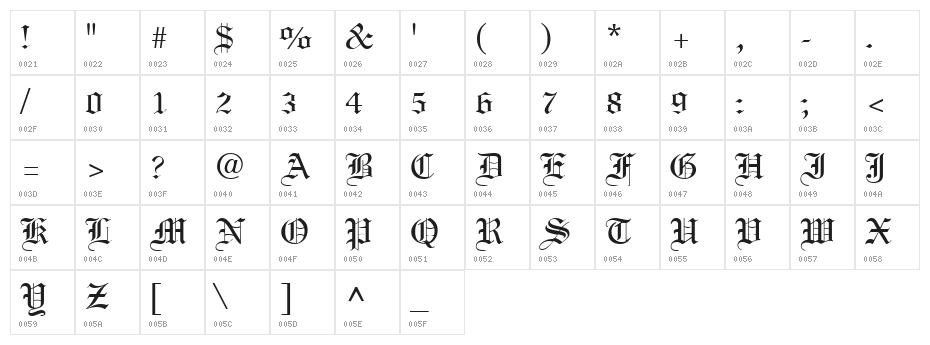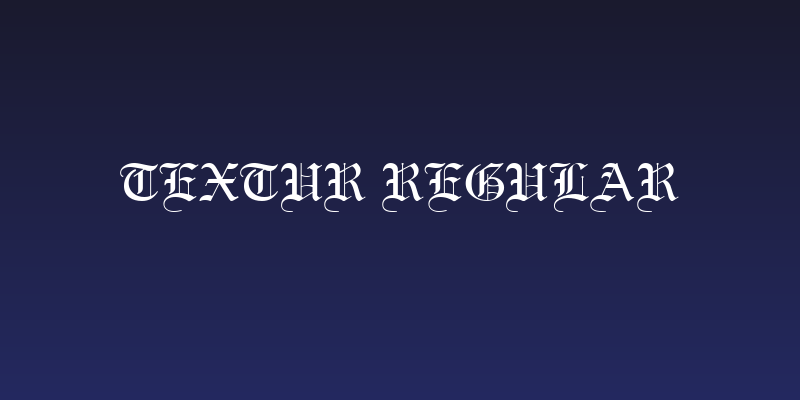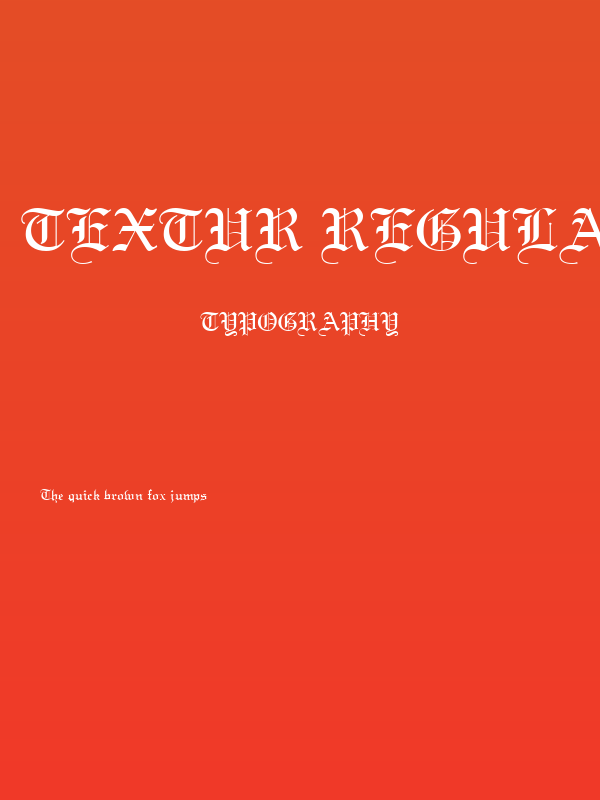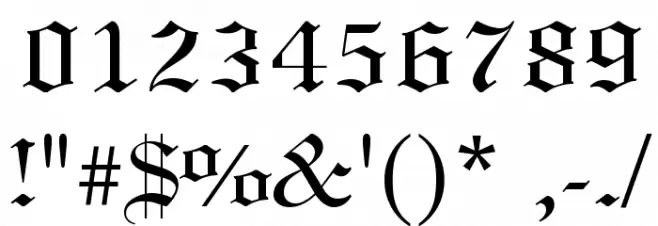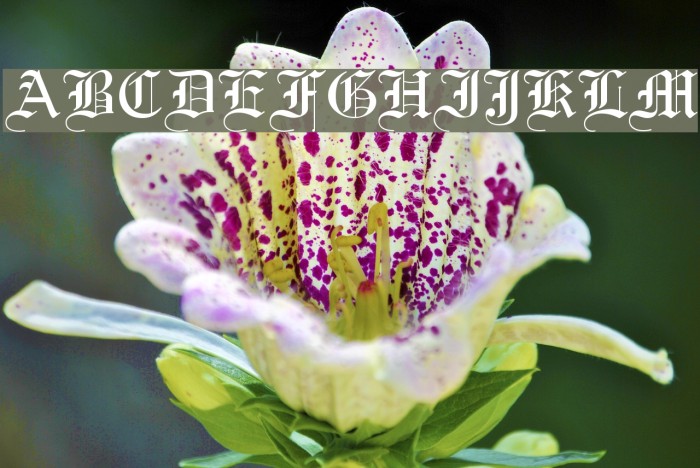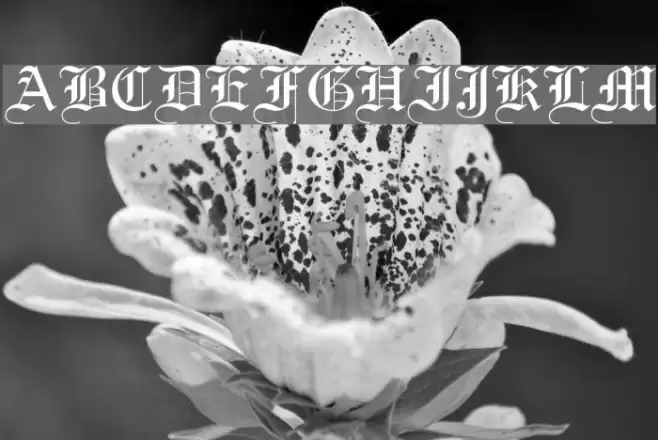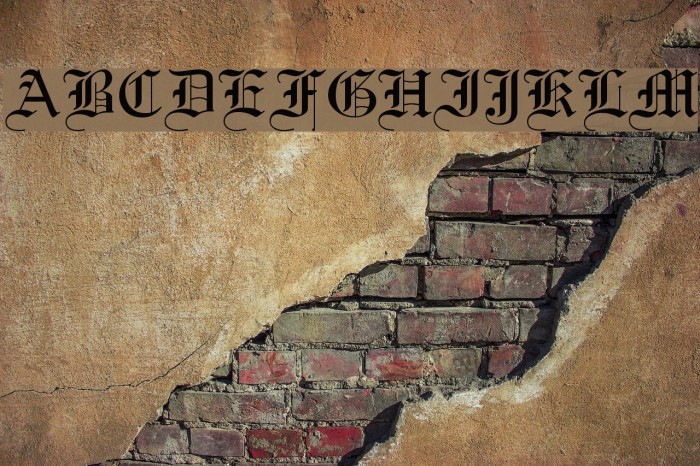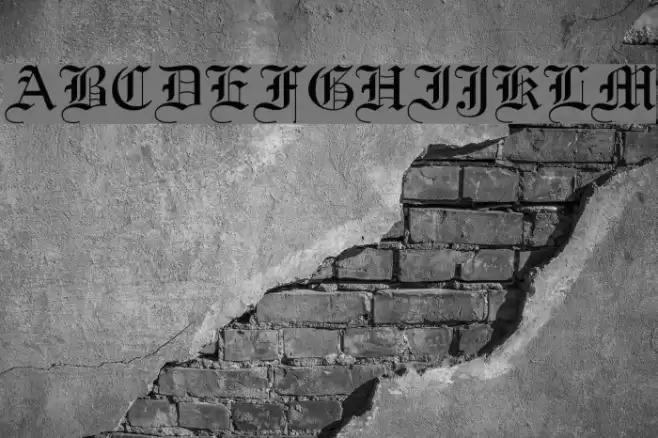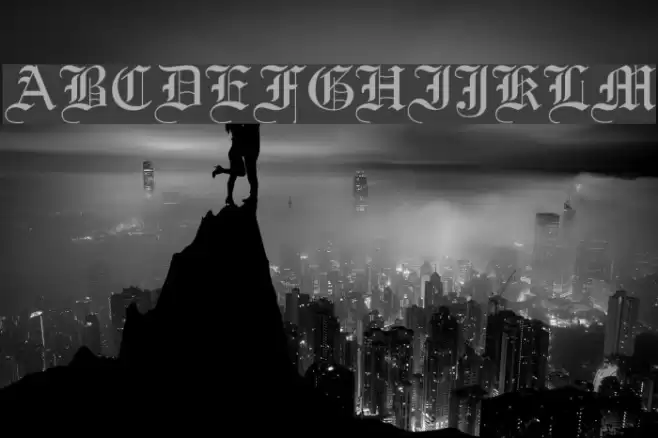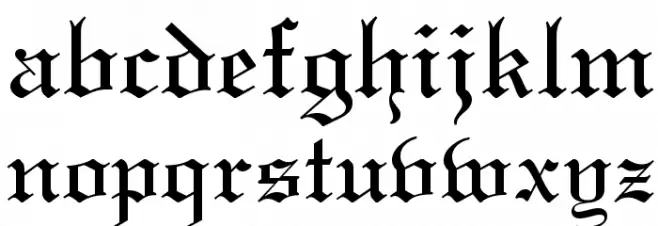
Textur Regular Font
✎ Gothic
| Категория | Gothic |
| Общий стиль | Vintage |
| Область применения | Logos, Headlines, Decorative text |
| Рекомендуемые проекты | Ideal for historical documents, wedding invitations, book covers, and branding that requires a classic touch. |